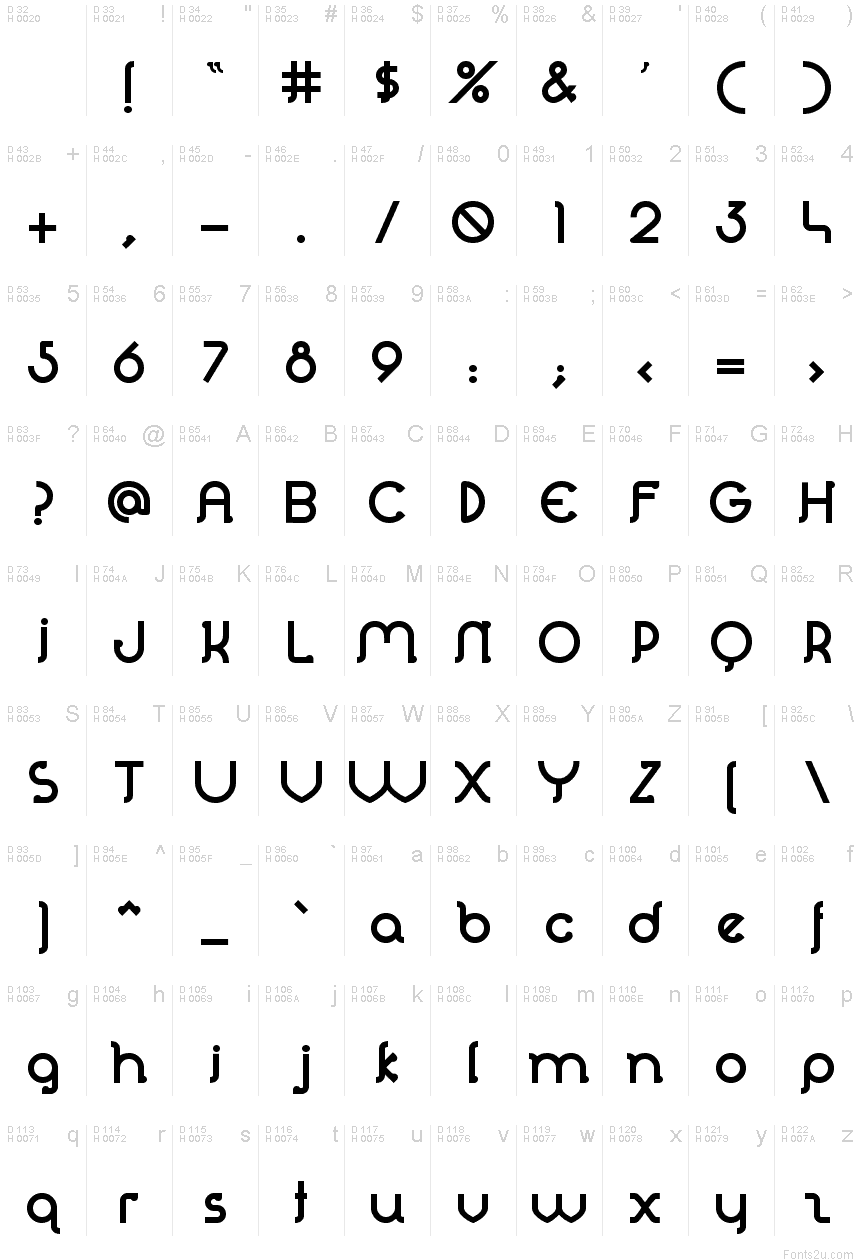
Perolet Bold, un font display moderno e gratuito, unisce forme circolari ampie a tagli netti che donano alle lettere un carattere retro-futurista ed elegante. Nonostante i tratti pesanti rimangano nel complesso morbidi e arrotondati, dettagli come l'intaglio diagonale della «e» e la «r» compatta e uncinata impediscono al design di apparire puramente geometrico.
Questo font gratuito è perfetto per titoli di poster, cover musicali, copertine di riviste, branding per il settore tech o della nightlife, e loghi brevi dove poche lettere bastano a dare il tono. Si adatta inoltre a cartelli di presentazione e monogrammi, poiché le sue ampie forme rotonde e i tagli angolari improvvisi creano rapidamente un ritmo visivo memorabile.